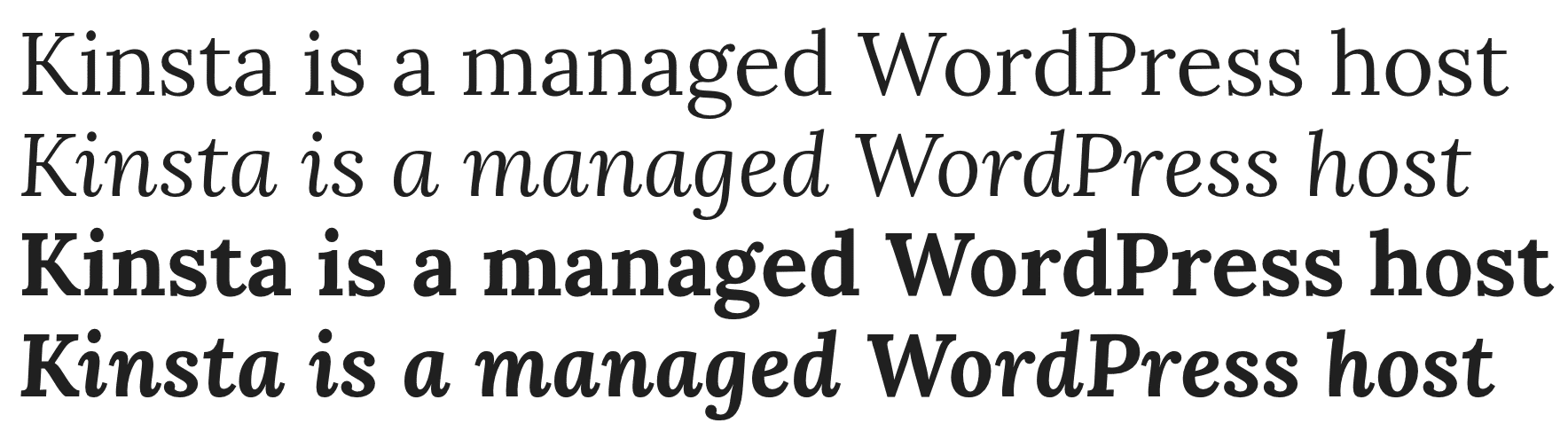
På det tidspunkt, hvor vi skriver denne artikel, er der 884 forskellige Google Font-familier tilgængelige gratis. Det er mange valgmuligheder! Derfor kan du være på udkig efter nogen, der hjælper dig med at finde den nål i en høstack, med en liste over de bedste Google Fonts.
Vi har det til dig, og så deler vi også nogle af de bedste fremgangsmåder til brug af Google Fonts på WordPress.
At vælge en skrifttype er mere end blot et æstetisk valg – det kan have en reel effekt på dit websteds afvisningsprocenter og konverteringsfrekvenser, især hvis du vælger en skrifttype, der er svær for dine besøgende at læse.
I bund og grund betaler det sig at tage lidt tid at vælge den bedste Google font-familie til dit websted, snarere end at bruge den første skrifttype, som du ser!
De 10 bedste Google-skrifttyper i 2019 – henhold til folkemængdenes visdom
Så hvordan kommer du op med en liste over de bedste Google Fonts, når så meget af dette er subjektivt? Vi ønsker ikke, at hele denne liste skal være subjektiv, så vi går til dataene for at opbygge en liste over de bedste Google Fonts.
Dybest set bruger vi Google Fonts-analytics for at stole på folkemængdenes viden. Med over 23 billioner i total skrifttypevisninger har Google bare en lille smule data at trække fra. 😉
Derefter går vi lidt ud over de rå popularitet tal og vælger nogle fremadgående skrifttyper, der vokser hurtigt. Parat? Lad os dykke ned i det…
1. Roboto
- Sans-serif
Roboto Google font
Roboto er et sans-serif tilbud fra Christian Robertson, som blev udviklet af Google som systemskrifttype til Android. Det er nu massivt populært, kommer i 12 forskellige stilarter og giver flere fremtoninger på Google Fonts ‘analyser. For eksempel er Roboto den mest populære skrifttype. Men Roboto Condensed er også den sjette mest populære skrifttype, og Roboto Slab har også et udseende på nummer 13!
2. Open Sans
- Sans-serif
Open Sans Google font
Open Sans er en sans-serif skrifttype udviklet af Steve Matteson. Google bruger Open Sans på nogle af sine hjemmesider såvel som i sine print- og webannoncer.
3. Lato
- Sans-serif
Lato Google font
Lato er et andet populært sans-serif-tilbud, denne gang fra Łukasz Dziedzic.
4. Slabo 27px/13px
- Serif
Slabo Google font
Slabo er en serif skrifttype udviklet af John Hudson af Tiro Typeworks. Hvad der er unikt med denne skrifttype er, at det er specielt designet til at blive brugt i en vis størrelse – enten 27px eller 13px afhængigt af dine behov.
5. Oswald
- Sans-serif
Oswald Google font
Oswald er en sans-serif skrifttype, der oprindeligt blev udviklet af Vernon Adams.
6. Source Sans Pro
- Sans-serif
Source Sans Pro Google font
Source Sans Pro er en sans-serif skrifttype fra Paul Hunt, der blev oprettet til Adobe og var Adobes første open source-font.
7. Montserrat
- Sans-serif
Montserrat Google font
Montserrat er en sans-serif skrifttype fra Julieta Ulanovsky, der bor i det mononymiserede Montserrat-kvarter i Buenos Aires. Med 18 forskellige stilarter har du ret mange valgmuligheder.
8. Raleway
- Sans-serif
Raleway Google font
Med 18 forskellige stilarter er Raleway en anden stor sans-serif skrifttype-familie, som oprindeligt blev oprettet af Matt McInerney. Hvis du kan lide Raleway og søger noget unikt, tilbyder Raleway Dots lignende styling med en prikket tilgang, som kan fungere for store overskrifter.
9. PT Sans
- Sans-serif
PT Sans Google font
PT Sans blev udviklet til den offentlige typografier af russiske føderation og omfatter som sådan både latin og cyrilliske tegn. Der er også flere andre skrifttyper i PT familien, herunder nogle serif muligheder.
10. Lora
- Serif
Lora Google font
Lora er en populær serif skrifttype, der er designet til at fungere godt både på din skærm og på print.
Bonus Fonter + Nyopkommende
Ved afstemning er de ti skrifttyper ovenfor, de mest populære Google Fonts. Men kun at vise de mest populære muligheder er ikke god service til store, fremadrettede skrifttyper, der ikke har fået eksponeringen til at dukke op på analyserne.
Her er nogle af vores favoritter, der ikke kom til udtryk øverst i analyserne.
11. Noto Sans / Serif
- Sans-serif or serif
Noto Sans Google font
Noto er en Google-commissioned skrifttype, der kommer i både serif og sans-serif versioner. Det modtager regelmæssige opdateringer, og der er nu godt over 100 Noto-skrifttyper, med flere på vej hele tiden!
Hvad er din foretrukne skrifttype af Google Fonts?
Google Font er fantastisk og bruges af millioner af hjemmesider på nettet hver dag. Følgende bedste praksis, som f.eks. Begrænsning af skrifttypevægte, og hosting af dem lokalt (i nogle tilfælde) og efter retningslinjer for tilgængelighed vil sikre en bedre samlet oplevelse for dine besøgende.